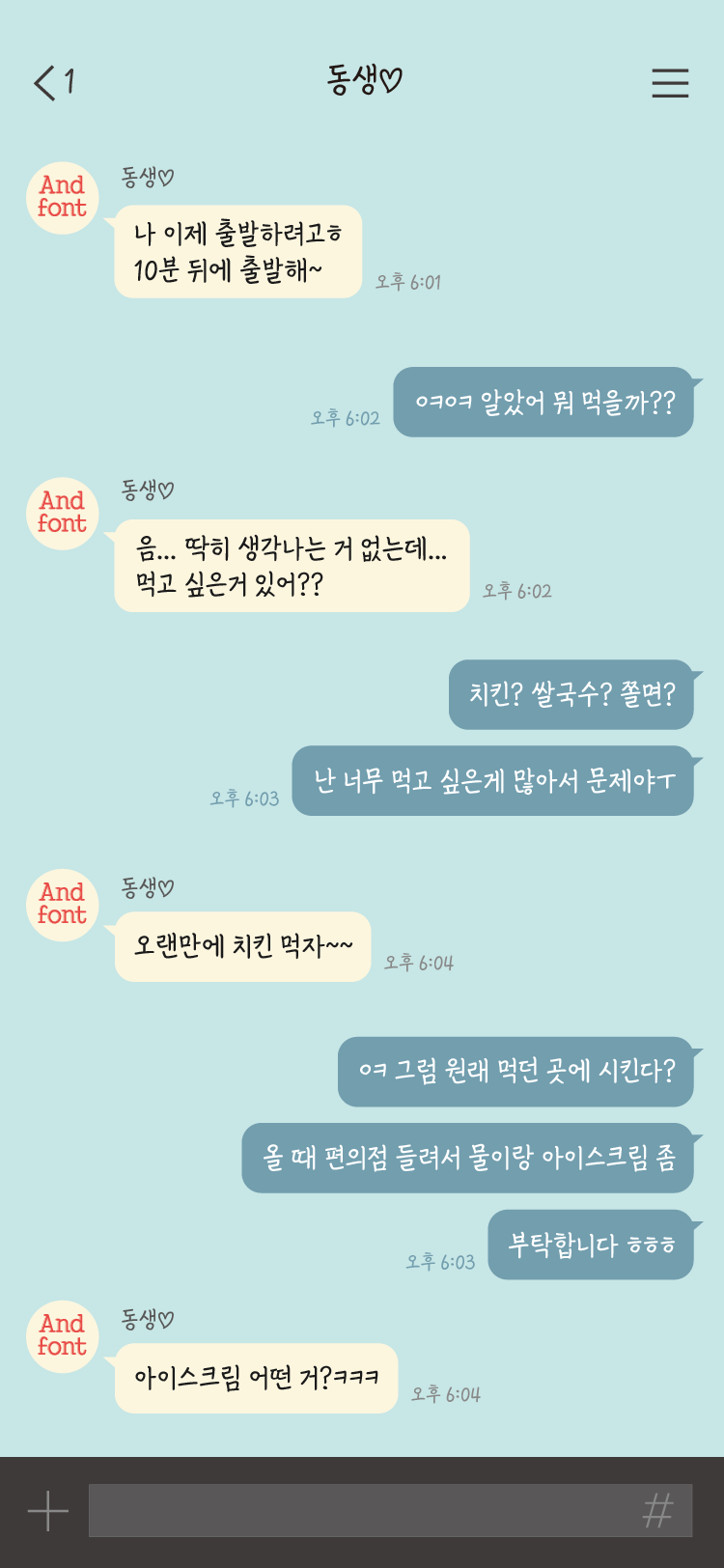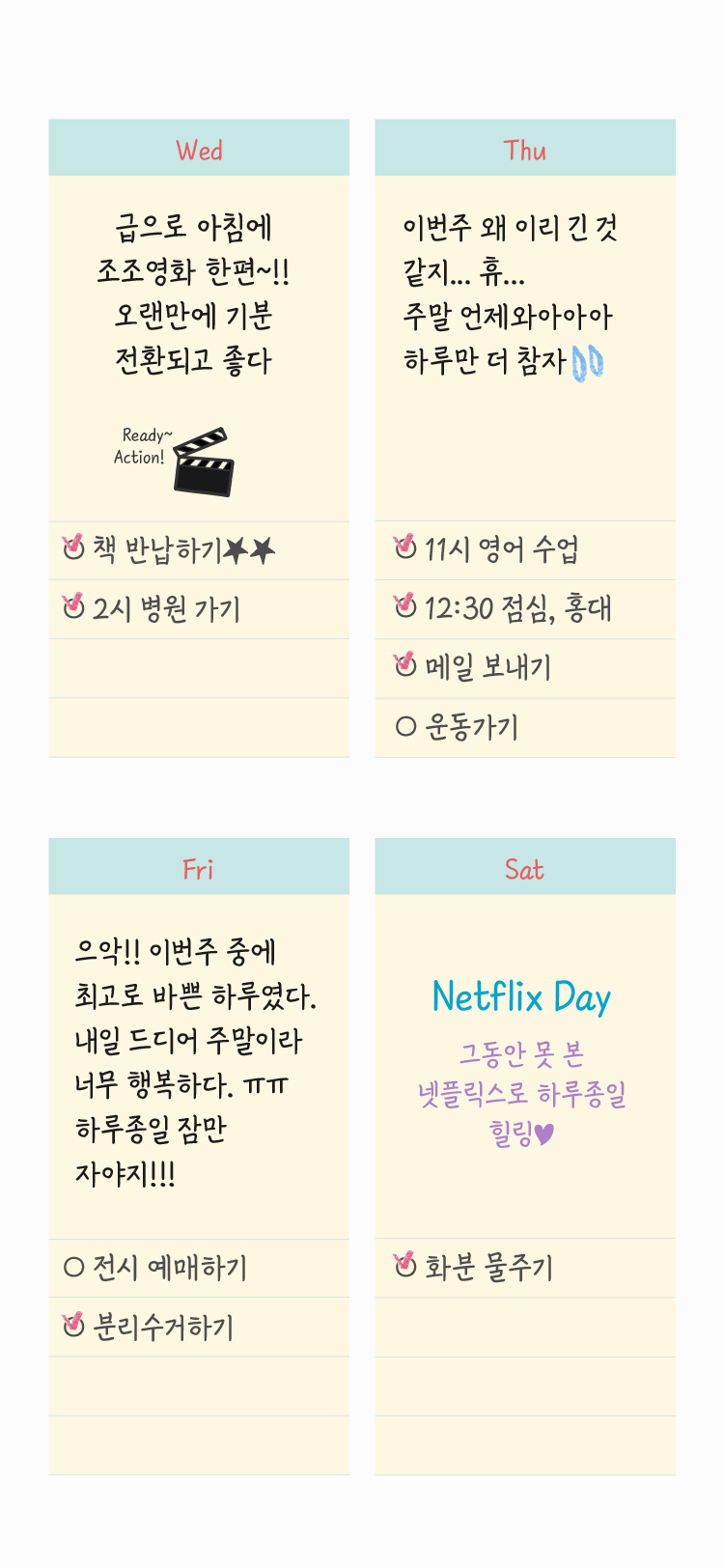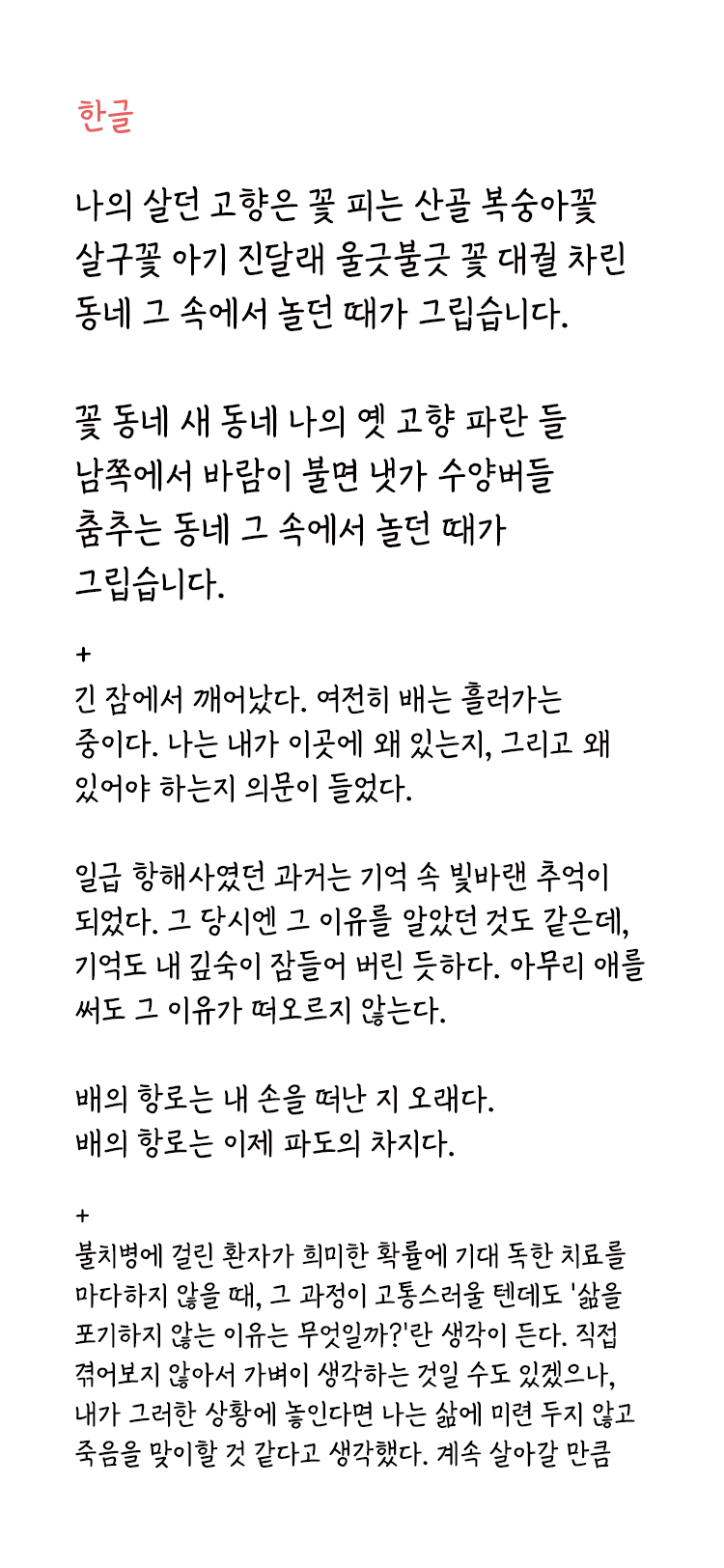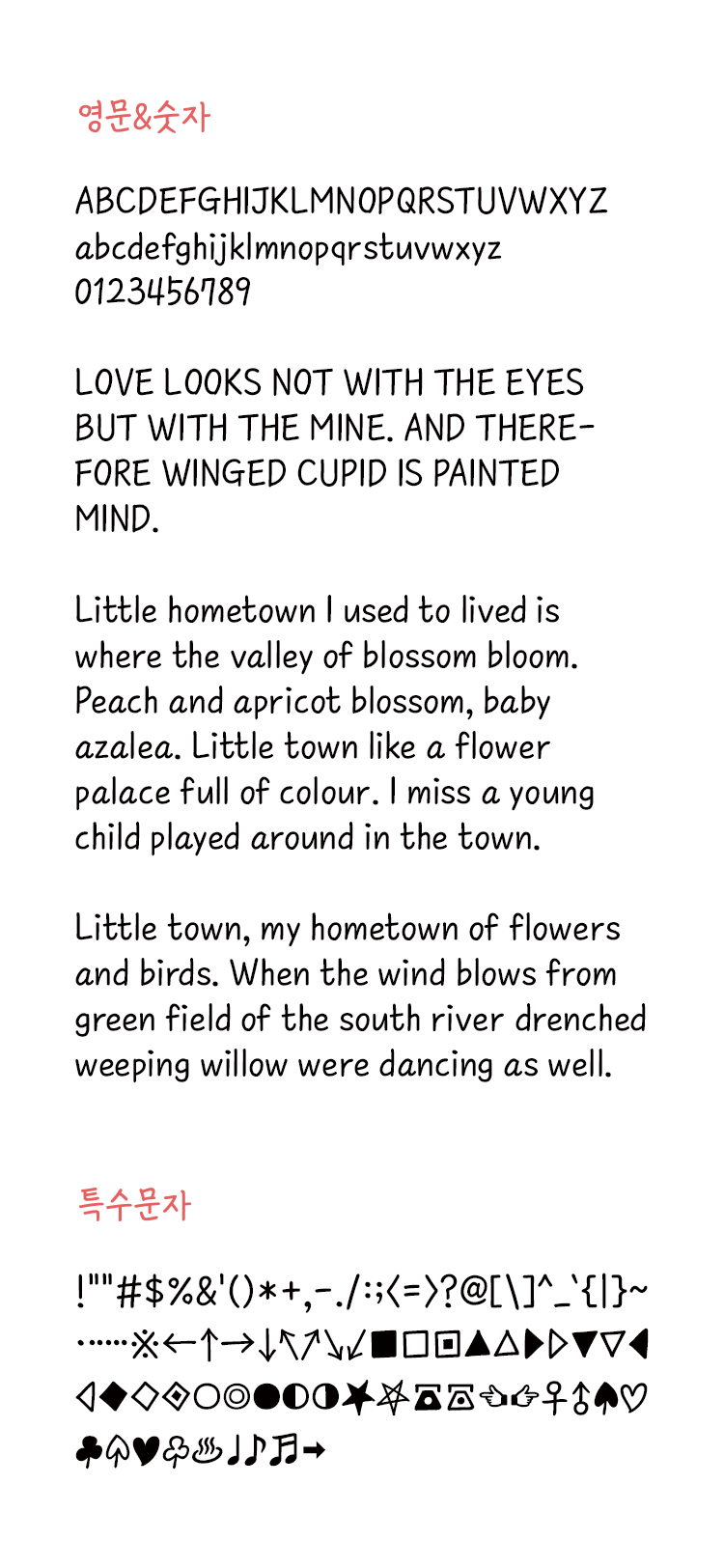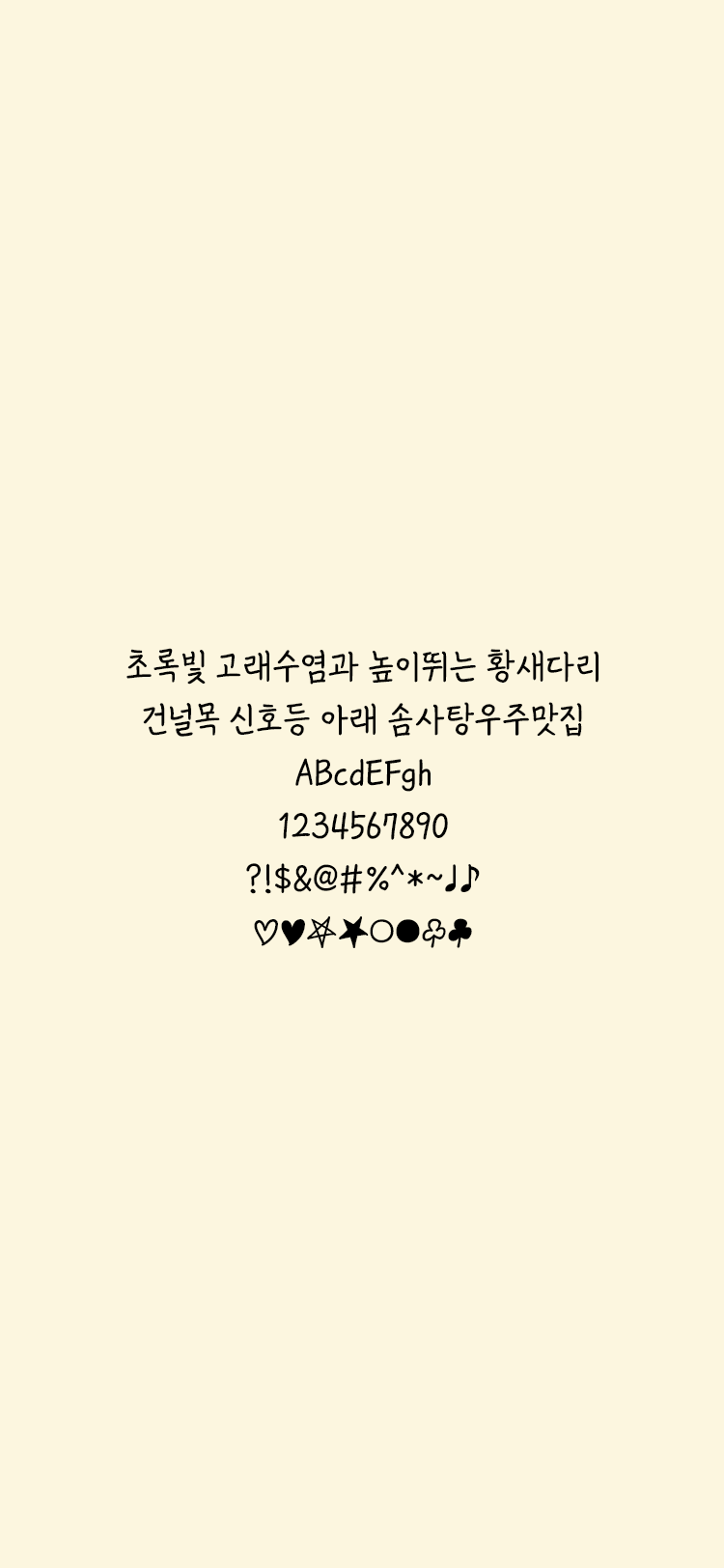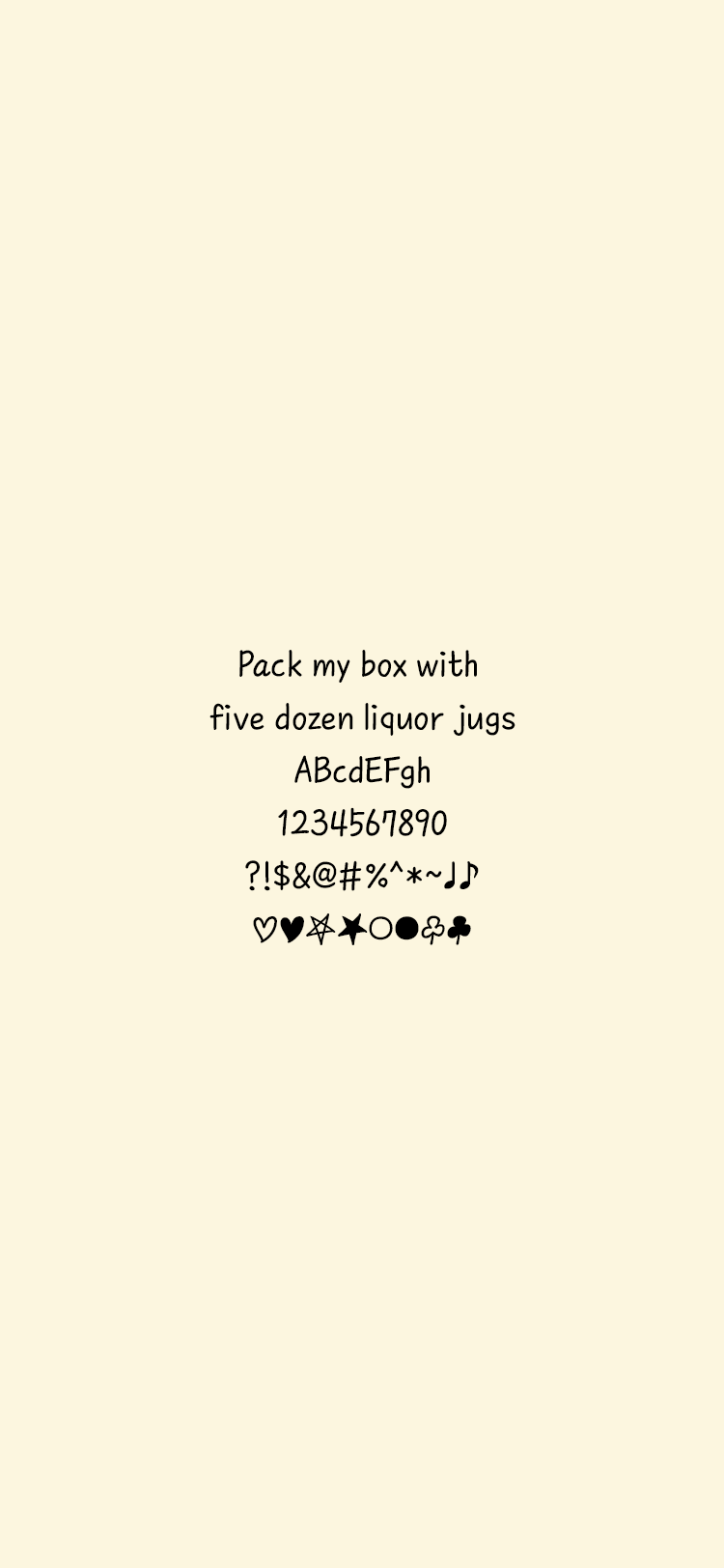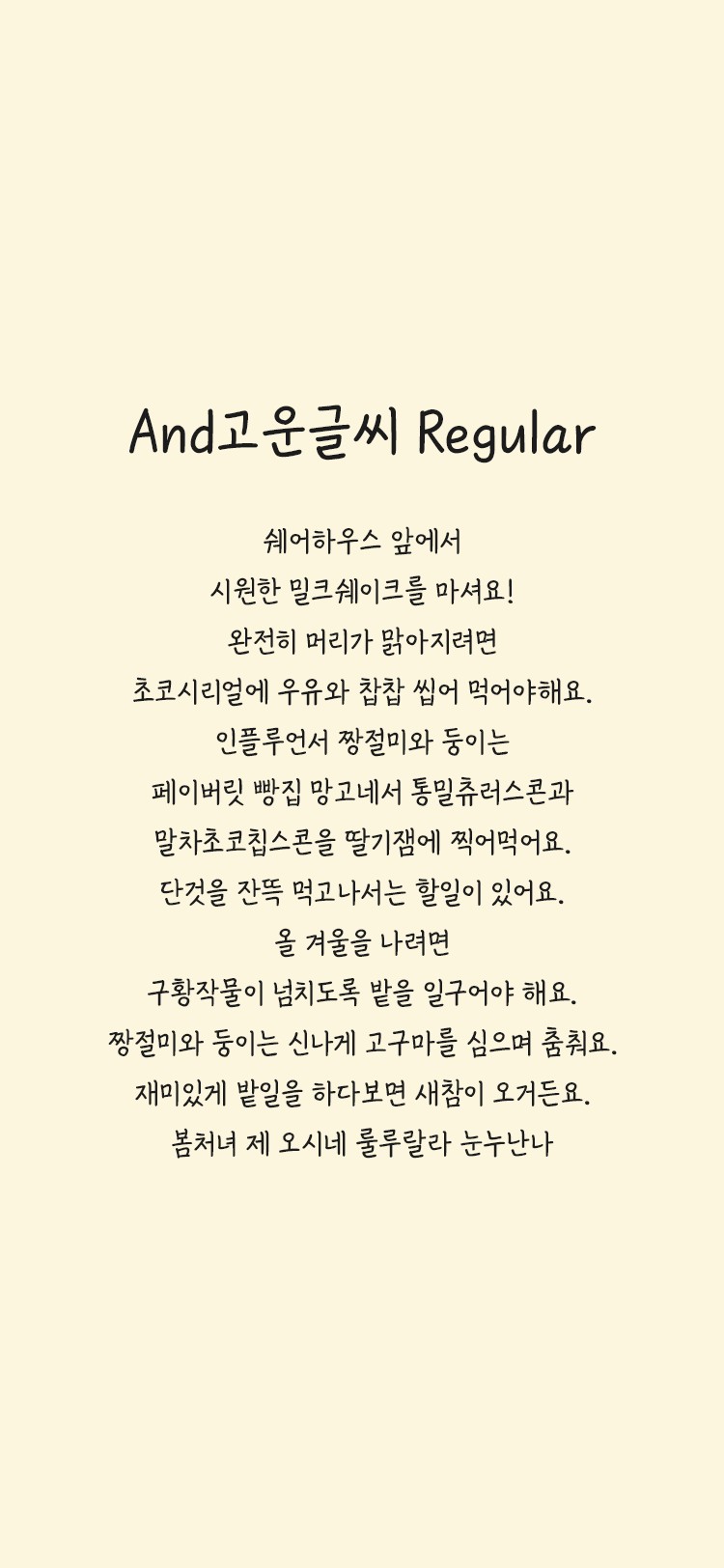
And고운글씨 M Regular
Andfont
And고운글씨 M Regular font in use
"고운글씨"는 정성스레 눌러 쓴 펜글씨입니다.
차분하고 감성적인 분위기를 원하는 곳엔 "고운글씨 Light"를,
진중하고 무게감이 필요한 곳엔 "고운글씨 Regular"를 사용해 보세요.
• And고운글씨 M Regular / AndFinetype M Regular